人気YouTuberのサムネイルでつかわれているようなグラデーション文字がつくりたいです!具体的なつくりかたをおしえてください!
- グラデーション文字のつくりかた
- 人気YouTuberのグラデーション文字を再現してみた
- 配色のまねかた【illustratorのスポイトツールつかいます】
人気YouTuberさんのサムネイルにつかわれているグラデーション文字ってめちゃくちゃ目立ちますよね。
たとえばこんな感じの文字です。
今回は私が人気YouTuberさんのサムネイルにつかわれているグラデーション文字を見よう見まねで再現してみました。
まったく同じとまではいえませんが、そこそこ再現できているのではないかと。
アピアランスの内容も公開しますのでよかったら参考にどうぞ。
線の太さは文字の大きさによって調整してください!
サムネイルに使える!グラデーション文字の作り方
人気YouTuberさんのサムネイルでつかわれているグラデーション文字を再現してみた
ヒカキンさんのグラデーション文字
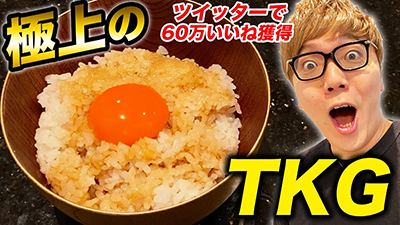
『極上の』の文字を分解すると
- 塗り:グラデーション
- 線:黒
- 線:白
こんな感じ。
これをもとに再現したのがこちら。
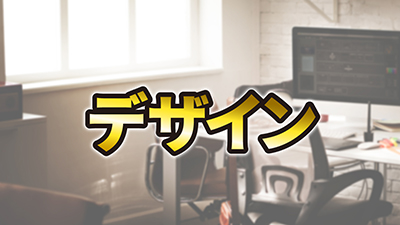
アピアランスとグラデーションをみてみると
上記のとおり。
グラデーションは両端から『濁りのある黄色』『黄色』『クリーム色』の順にならべ、角度は『 -100°』に設定。
中田敦彦さんのグラデーション文字
『経済的自立』の文字を分解すると
- 塗り:グラデーション
- 線:濃い緑
- 線:黄緑
- 線:濃い緑
こんな感じ。
これをもとに再現したのがこちら。
アピアランスとグラデーションをみてみると
上記のとおり。
グラデーションは左端から『黄色』『白色』『薄い黄色』の順にならべ、角度は『 95°』に設定。
境界線がはっきりしたグラデーションは、グラデーションスライダーにあるポイントとポイントを近づけてつくります。
ラファエルさんのグラデーション文字
『ランボ勝手に全塗装』の文字を分解すると
- 塗り:グラデーション
- 線:黒
- 線:白
こんな感じ。
これをもとに再現したのがこちら。
アピアランスとグラデーションをみてみると
上記のとおり。
グラデーションは両端が『オレンジ色』中央が『黄色』の順にならべ、角度は『 -90°( 90°も可)』に設定。
宮迫博之さんのグラデーション文字
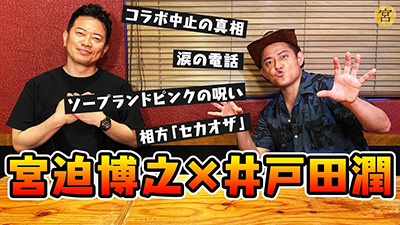
文字を分解すると
- 塗り:グラデーション
- 線:黒
- 線:白
こんな感じ。
これをもとに再現したのがこちら。
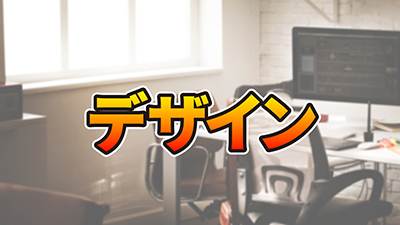
アピアランスとグラデーションをみてみると
上記のとおり。
グラデーションは『濃いオレンジ色』と『濃い黄色』の組みあわせ、角度は『 90°』に設定。
両学長さんのグラデーション文字
文字を分解すると
- 塗り:グラデーション
- 線:白
- 線:赤 or 青
- 線:白
こんな感じ。
これをもとに再現したのがこちら。
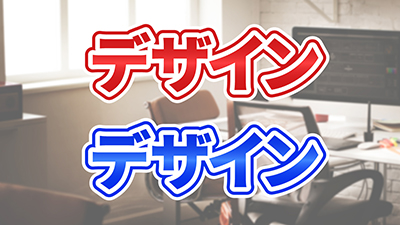
赤色のアピアランスとグラデーションは
上記のとおり。
グラデーションは両端が『赤色』で真ん中が『薄い赤色』の組みあわせ、角度は『 -90°( 90°も可)』に設定。
青色のアピアランスとグラデーションは
上記のとおり。
グラデーションは両端が『青色』で真ん中が『薄い青色』の組みあわせ、角度は『 -90°( 90°も可)』に設定。
マコなり社長さんのグラデーション文字
『話し方』の文字を分解すると
- 塗り:グラデーション
- 文字:ドロップシャドウ
こんな感じ。
これをもとに再現したのがこちら。
アピアランスとグラデーションをみてみると
上記のとおり。
グラデーションは両端が『オレンジ色』中央が『黄色』の順にならべ、角度は『 -150°』に設定。
マナブさんのグラデーション文字
『800万円』の文字を分解すると
- 塗り:グラデーション
- 線:グラデーション
- 線:黒
こんな感じ。
これをもとに再現したのがこちら。
アピアランスと『塗り』のグラデーションをみてみると
上記のとおり。
グラデーションは左端から『オレンジ色』『黄色』『白色』の順にならべ、角度は『 90°』に設定。
また『線』のグラデーションは
上記のとおり。
グラデーションは『オレンジ色』と『黄色』の組みあわせ、角度は『 -90°』に設定。
配色のまねかた【illustratorのスポイトツールつかいます】
いろいろなサムネイルをみていると『すてきな配色だな』と思うことありますよね。
そんなときはillustratorのスポイトツールで色を抽出してみましょう。
スポイトツールをつかって気になる色を抜きだし、自分のサムネイルに応用することで貴重な勉強をすることができますよ。